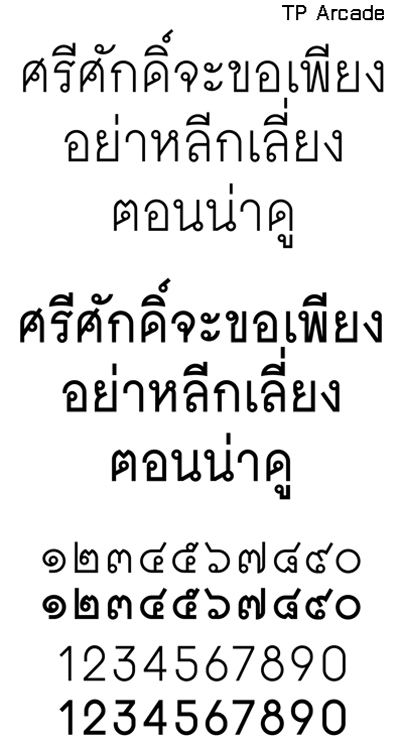
FONT Compitition
แล้วก็จะได้ทำจนครบ มาแจกที่นี่ล่ะนะ
แต่คาดว่าคงอีกนานแฮะ
ฟอนต์พี่ทิพย์สวยจังค่ะทั้งฟอนต์ทั้งคนทำ  :21:
ปล.ในใจแล้ว ผมว่าฟอนต์พี่ทิพย์สวยกว่าผมอีก มีเอกลักษณ์
ฟอนต์ผมมันออกแนวโหลๆไงนี่แหละ จนตัวเองยังขี้เกียจทำต่อเลย :08:
ของทิพย์ดูจะติดนิสัยของ Cordia มาหน่อยนึงนะ
เพราะดูจากสัดส่วนเอย อวัยวะเอย (ไม่รู้เขาเรียกกันว่าไง)
มันจะดูคลายกับว่าเอา Cordia มาแปลงน่ะ
ในขณะที่ของห้าโอดูมันกวนตีนกว่า
เพราะดูไม่เหมือนฟอนต์ดัดแปลง
นี่พูดตรงไปไหมฟะ
font ของปลาวาฬ ดู OK นะครับ
ผมเดาจากคราวที่แล้วนะครับ ว่าอาจจะเป็นเพราะว่า
การคัดเลือกคือเค้าจะแบ่งประเภทของ font
ว่าประมาณไหน เช่น ดูเรียบร้อย ดูทันสมัย ดูไทย ดูร่วมสมัย ดูแปลกใหม่ ดู....ฯลฯ
ซึ่งแบบที่คุณวาฬทำมาอาจจะต้องแข่งขันสูงหน่อย
เพราะคนทำงานออกแบบส่วนใหญ่มักจะใช้ font ที่ทันสมัยเรียบง่าย
เช่น tom light (cordia) -> db fongnum -> db soda
น่าจะมีคนส่งประมาณนี้เยอะเอาการนะครับ
เพราะเป็น font ที่ถูกคิิขึ้นใหม่นี่ครับ
ของคราวที่แล้วยังไม่ได้เห็นของใครเลยครับ
นอกจาก 10 ตัวสุดท้าย
คราวนี้ผมว่าก็คงเหมือนเดิมครับ
อ๊ะ แสดงว่าใครที่ตกรอบคราวนี้
ถ้ามีประกวดคราวหน้าอีกก็สามารถเอามาปรับปรุงแล้วลองส่งดูใหม่ได้อีกทีใช่ไหมครับ
แล้วจานเอกเป็นกรรมการด้วยหรือว่าส่งประกวดกับเขาหรือเปล่าครับ
ป.ล. สรุปว่าพี่ห้าโอเข้ารอบสินะครับ อดฟอนต์เลยสิเนี่ย  :11: ไง ๆ ก็เอากล่อง FontLab มาให้ชาวฟอนต์ได้เชยชมกันให้ได้นะครับพี่!!!  :12: